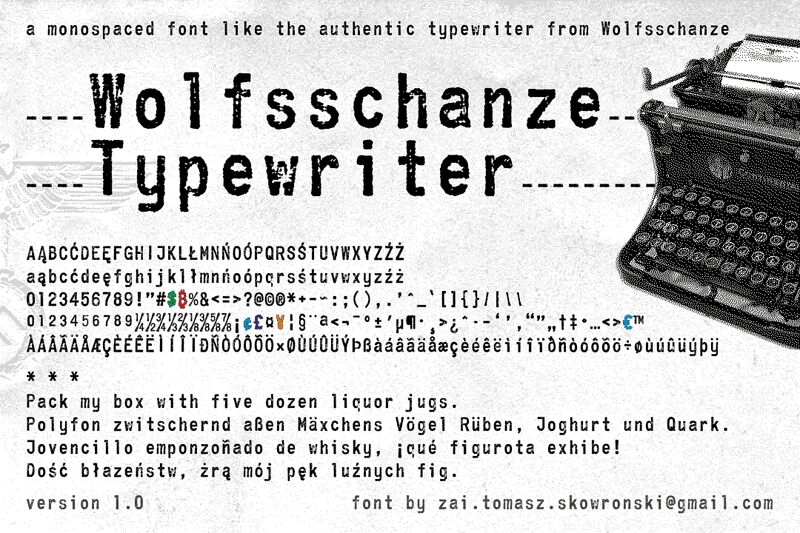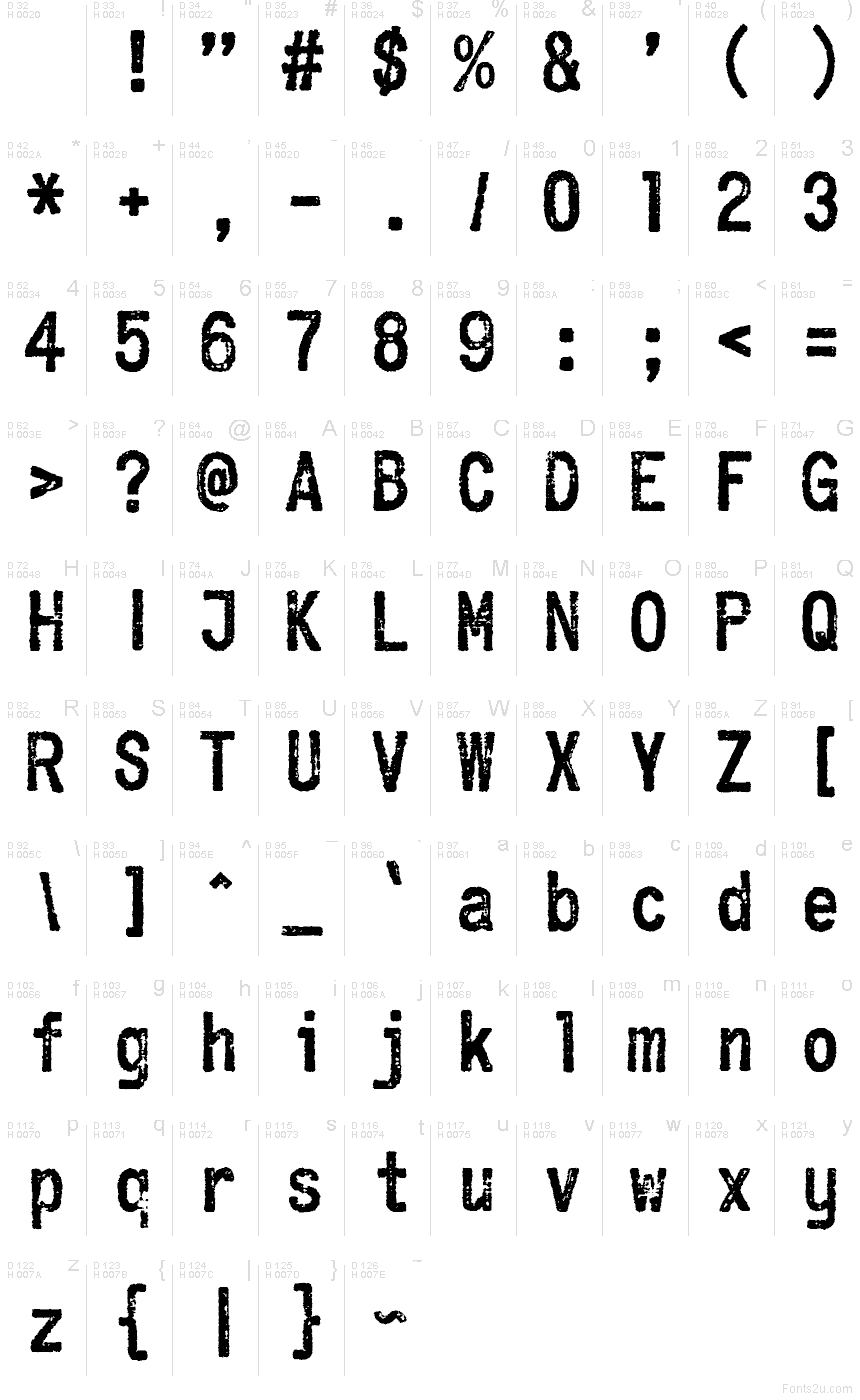
zai Wolfsschanze Typewriter
Zai Wolfsschanze Typewriter es una tipografía gratuita de estilo máquina de escribir antigua, con el acabado sucio y cargado de tinta propio de una máquina que ha visto tiempos mejores. Las letras parecen estampadas en lugar de dibujadas, con bordes irregulares, una textura desgastada y un ritmo pesado y castigado que recuerda más a archivos de búnker que a una oficina moderna.
Esa fuerza bruta la hace perfecta para pósteres bélicos, fanzines underground, títulos de películas, menús de juegos o portadas de discos donde quieras que el texto se sienta real y gastado. Al ser una fuente gratuita, también funciona muy bien en titulares cortos, aperturas de capítulos o diseños con estética de dossier, porque la textura de máquina de escribir antigua transmite la atmósfera antes de que necesites muchas palabras.